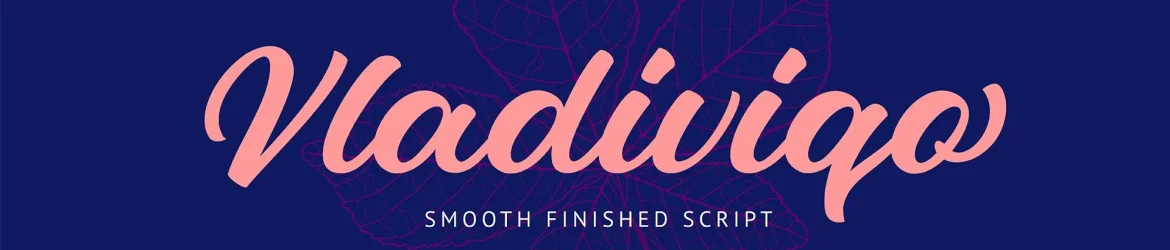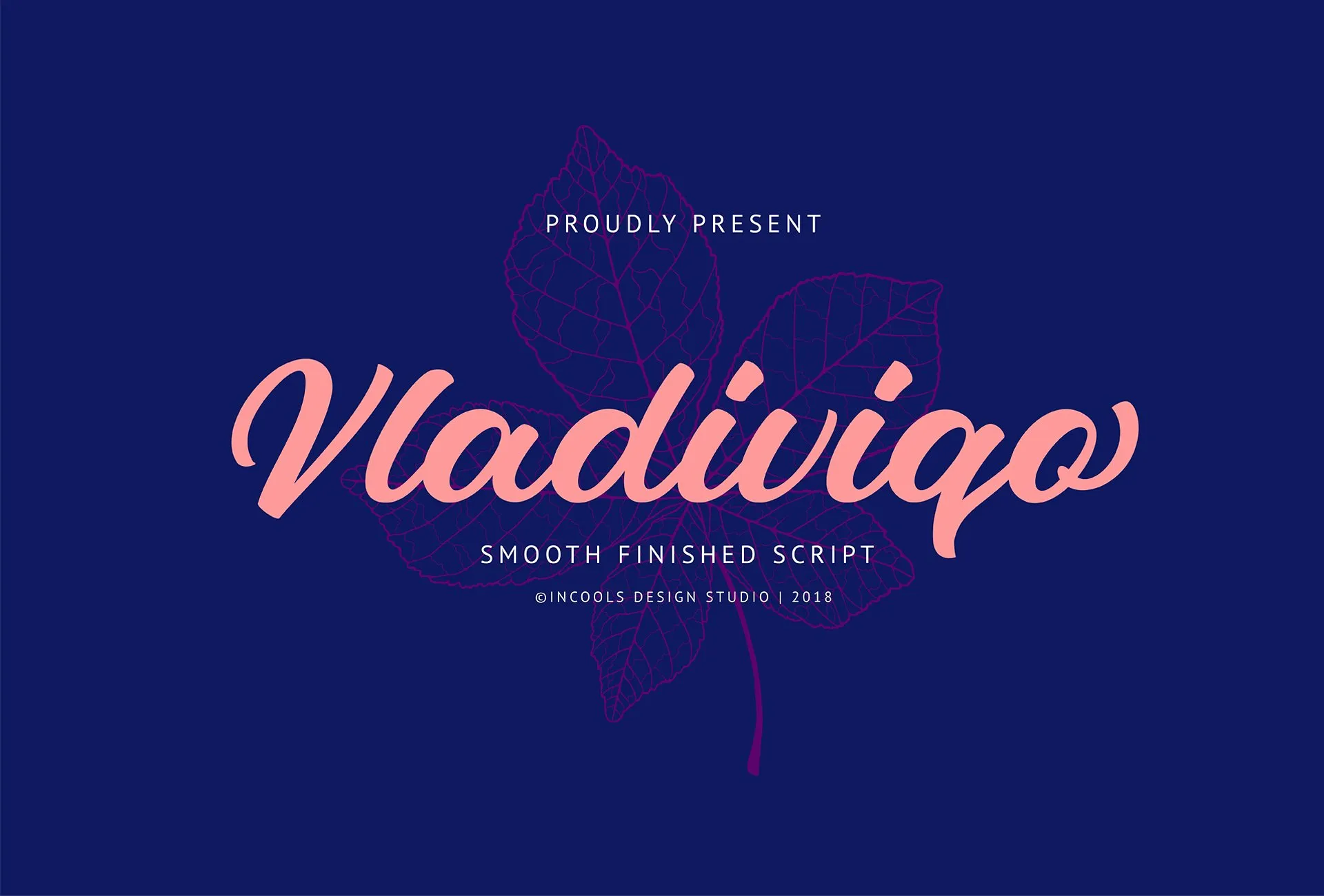
Vladiviqo Script Font – Fonte Grátis
Vladiviqo Script Font
Introduzimos a Vladiviqo Font, uma elegante tipografia script cuidadosamente criada com todo amor. Com suas letras maiúsculas e minúsculas limpas, sua finalização suave e seus símbolos de pontuação, é um recurso indispensável para designers gráficos. Este conjunto completo inclui alternativas personalizadas que garantem a máxima versatilidade na criação do seu próximo projeto. O designer zziplex dedicou-se em criar uma fonte que se destaca por sua delicadeza e clareza, perfeita tanto para textos singulares quanto para fins publicitários. Se você busca um estilo elegante e personalizado, a Vladiviqo Font é definitivamente o elemento ideal para seu trabalho de design.